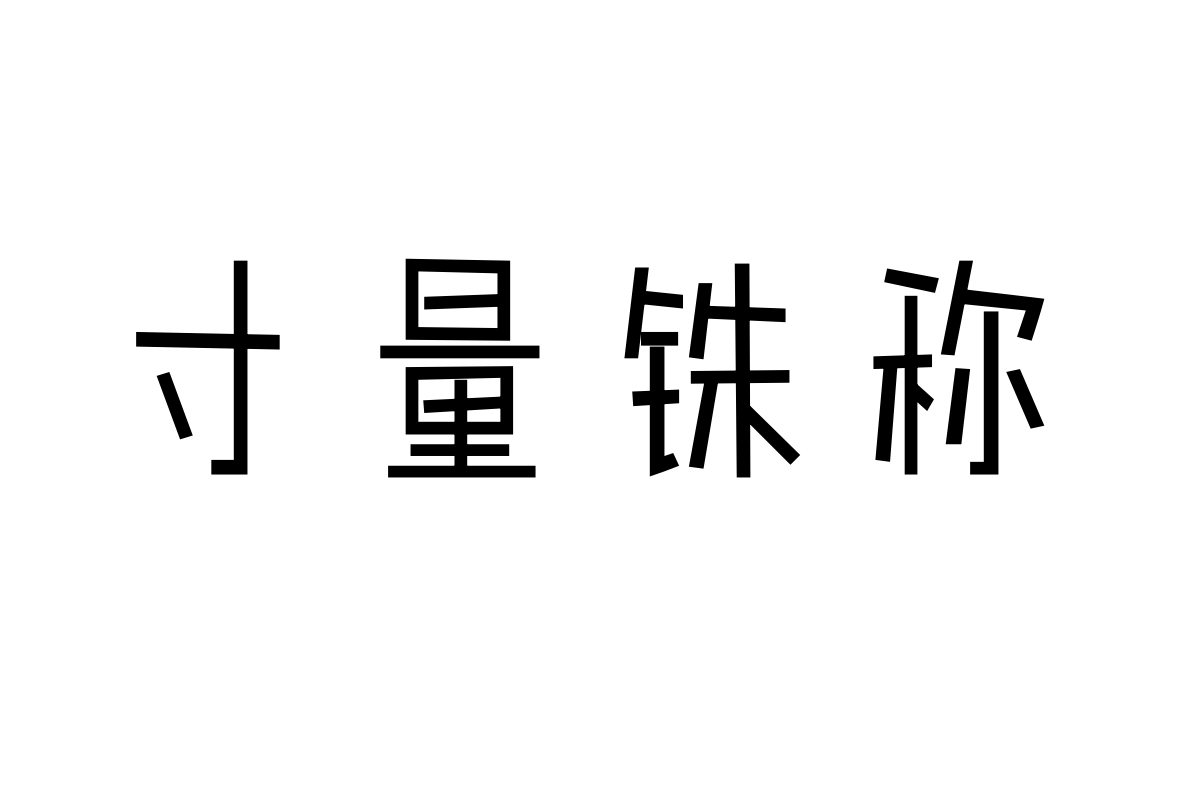
汉仪二次元达人简是一款专为二次元动漫设计的文字字体,具有独特的风格和特点。这款字体线条流畅、粗细适中,给人一种轻盈的感觉,非常适合用于二次元动漫的标题、角色名称等场景。同时,它的笔画简洁明了,易于书写和识别,使得整体效果更加美观。此外,汉仪二次元达人简还具有一定的可读性,能够清晰地传达出文字的含义,满足二次元动漫中对于文字清晰度的要求。总的来说,汉仪二次元达人简是一款非常优秀的二次元动漫文字字体。